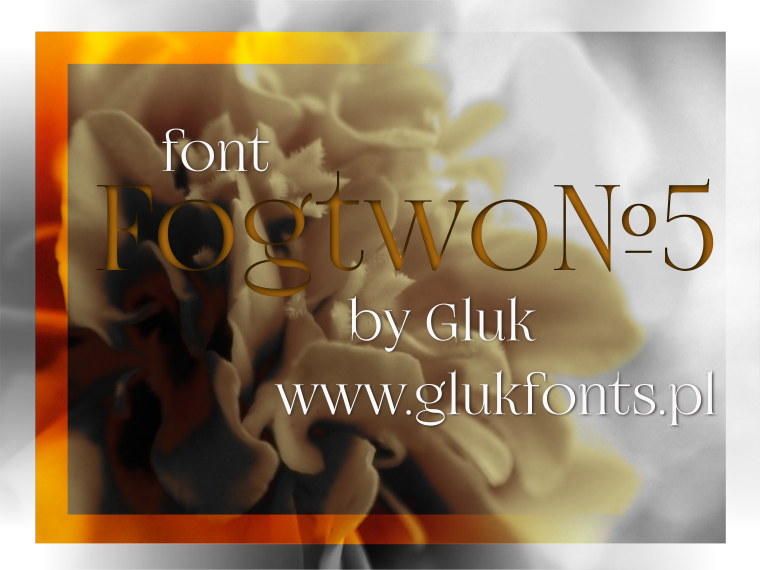
Agora está disponível uma nova fonte serif chamada FogtwoNo5 para quem busca uma opção elegante e decorativa para seus projetos de design. Inspirada na popular Foglihten, a FogtwoNo5 é perfeita para aplicações onde um toque de sofisticação se destaca, como editoriais de revistas, materiais de publicidade ou design gráfico tradicional. Esta fonte serif oferece um charme clássico e moderno ao mesmo tempo. Suas linhas decorativas são acentuadas com detalhes interessantes que adicionam um toque único e personalizado aos seus projetos. Ideal para títulos de páginas ou subtítulos, ela será certamente o complemento perfeito para qualquer projeto que deseje exibir um ar elegante. Embora a original Foglihten tenha sido concebida com uma aparência mais moderna e futurista, a FogtwoNo5 mantém sua essência de design sem perder seu charme característico. Seja para criar uma identidade visual única ou para estilizar um texto de forma elegante, esta fonte serif é certamente uma escolha inteligente. Sem dúvida, ela trará um toque especial à sua próxima produção gráfica.